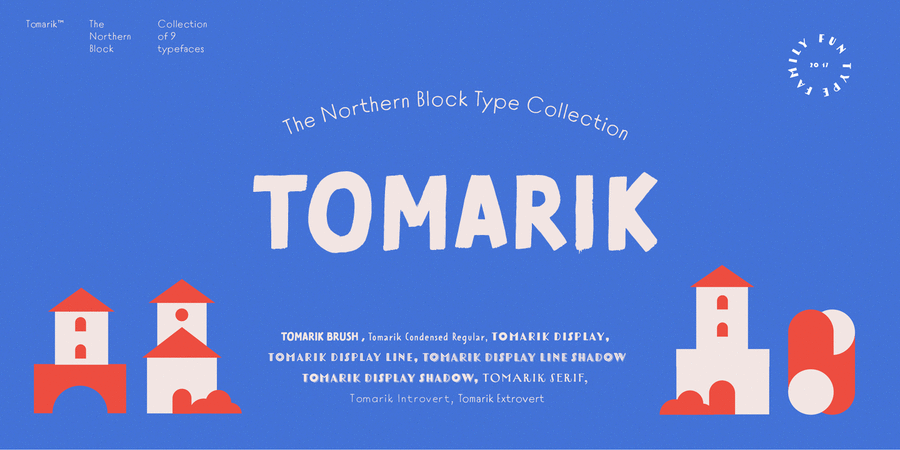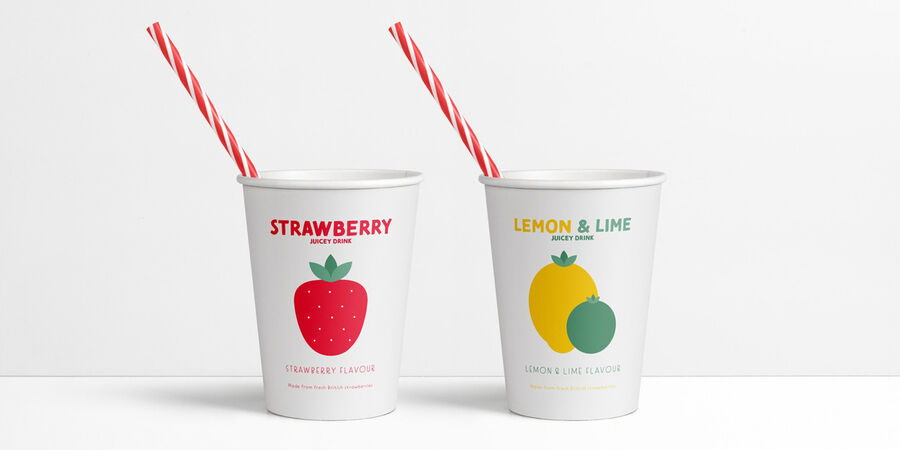
Опис шрифта Tomarik BrushПростий гротеск, написаний пласким пензлем – частина яскравої колекції рукописних шрифтів Томарік. Грайливе доповнення будь-якого творчого проекту. Шрифтової набір, зібраний для роботи за принципом «обирай і змішуй», він пропонує велику різноманітність стилів і характерів. Томарік містить дев'ять різних накреслень з латинкою та кирилицею і включає функції OpenType, такі як верхні та нижні індекси і дроби. Шрифт розробила Марія Пігулевська у 2017 році. Tomarik™ є торговою маркою компанії The Northern Block.
вуличний, міський, неформальний, ручний, саморобний, помітний, домашній, ремісничий, артізанальний, кричущий, вернакулярний, свіжий, зрозумілий, ясний, зелений, природний, органічний, натуральний, знайомий, переконливий, політичний, Простий, мотивуючий, амбітний, зимовий, здоровий, бадьорий, студентськиий, динамічний, позитивний, вільний, сміливий, гучний, яскравий, значний, впевнений, сильний, стійкий, революційний, робочий, андеграундний, гаражний, нерівний, чесний, екологічний, фермерський, побутовий, вінтажний, працьовитий, добротний, теплий, ламповий, консервативний, рішучий, грубий, рукотворний, доступний, кустарний, крафтовий, осінній, лісовий
хенд мейд, відпочинок, природа, анімація, закуска, торгівля, крамниця, базар, Місто, дерево, прапор, політика, зима, Інстаграм, фаст фуд, вечірка, магазин, гра, табір, гумор, їжа, шоу, мітинг, революція, відео, страйк, Протест, ремесло, м'ясо, реклама, монстр, ярмарок, деревина, осінь, чіпси, фарба, ферма, фермер, запас, склад, ящик, тесля, вечеря, гамбургер, соус, кетчуп, шаурма, обід, інструмент, селфі, графіка, ілюстрація, дім, небо Гарнітура асоціюється з віком: